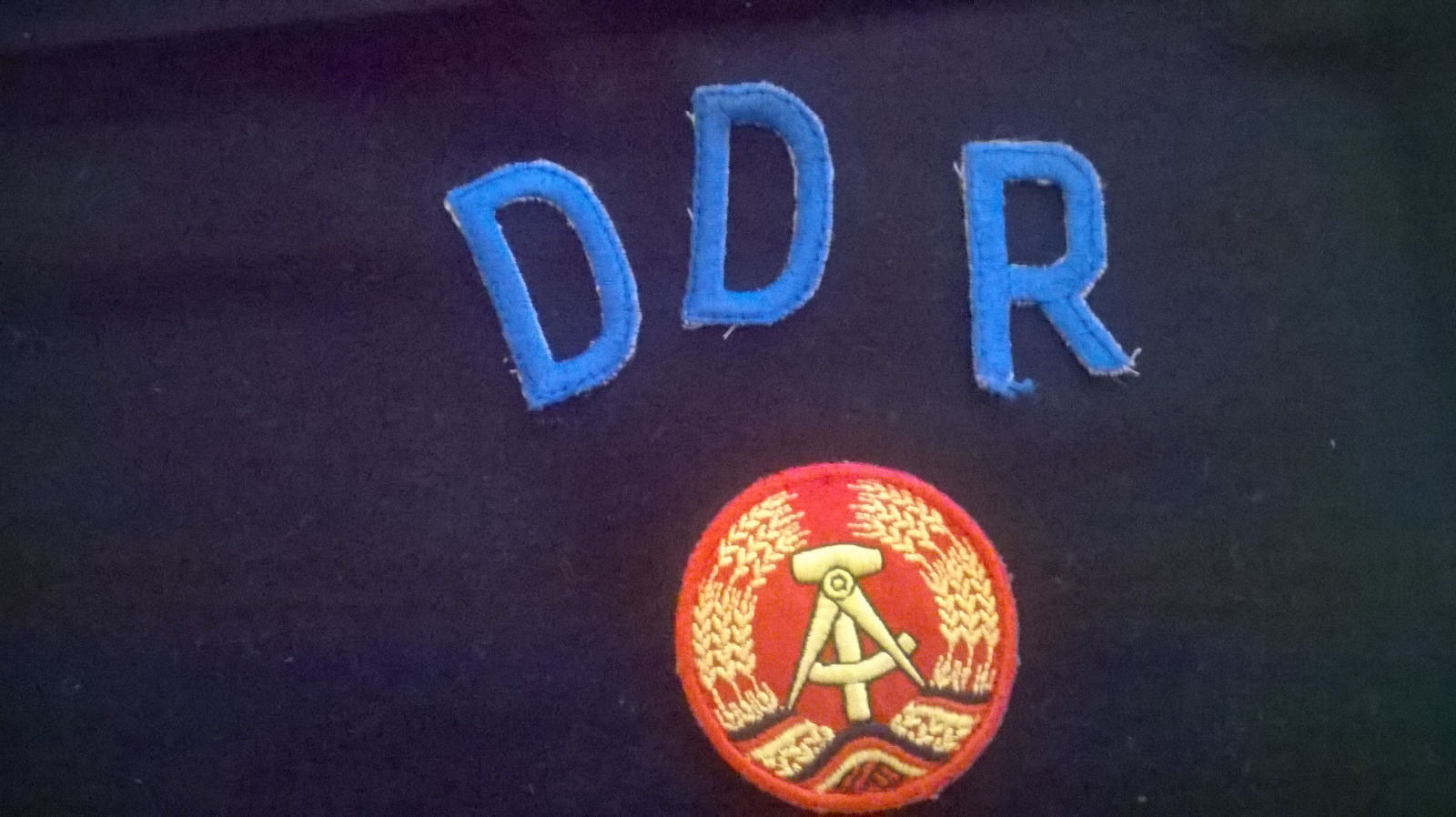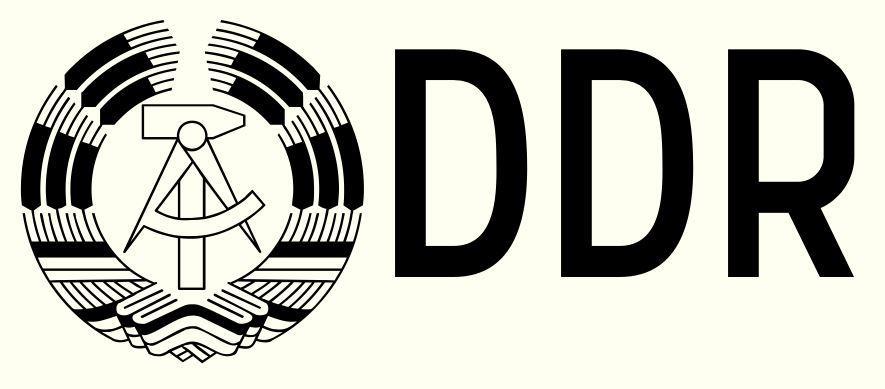
Suche Schrift (Trikot DDR)
ich such die Schrift zum Trikot der DDR. Anbei seht Ihr ein Beispielbild. Das "R" habe ich leider nirgends gefunden. Vielen Dank vorab :)
Das "D" ist ja relativ häufig zu finden. Jedoch habe ich das "R" nirgends in der Art finden können. Also mit dem im Vergleich großen "Kreis zum kurzen Rest des Buchstaben.
Dann solltest du dir diese zwei Buchstaben im Illustrator doch leicht selbst nachbasteln können, statt extra eine Schrift zu kaufen ...
Ich konnt's mir jetzt nicht verkneifen, und habe mal schnell ne 1-Stunden-Schrift gebaut, mit dem DDR-Wappen auf 0 und @ (das hatte ich schon für ne andere Schrift gebaut) und dann, ausgehend von D und R, die anderen Großbuchstaben (sorry, noch kein ẞ, aber kommt noch, vielleicht :-)
Damit dürfte sich das Problem, das in Illustrator nach zu bauen wohl erledigt haben, oder?
Hatt ich nicht die Idee gehabt, noch die anderen Buchstaben da hinzu zu erfinden, wär's tatsächlich ne 5 Minuten-Schrift (mit den 2 gesuchten Buchstaben) geworden, aber nur mit D und R war's mir dann doch zu dumm